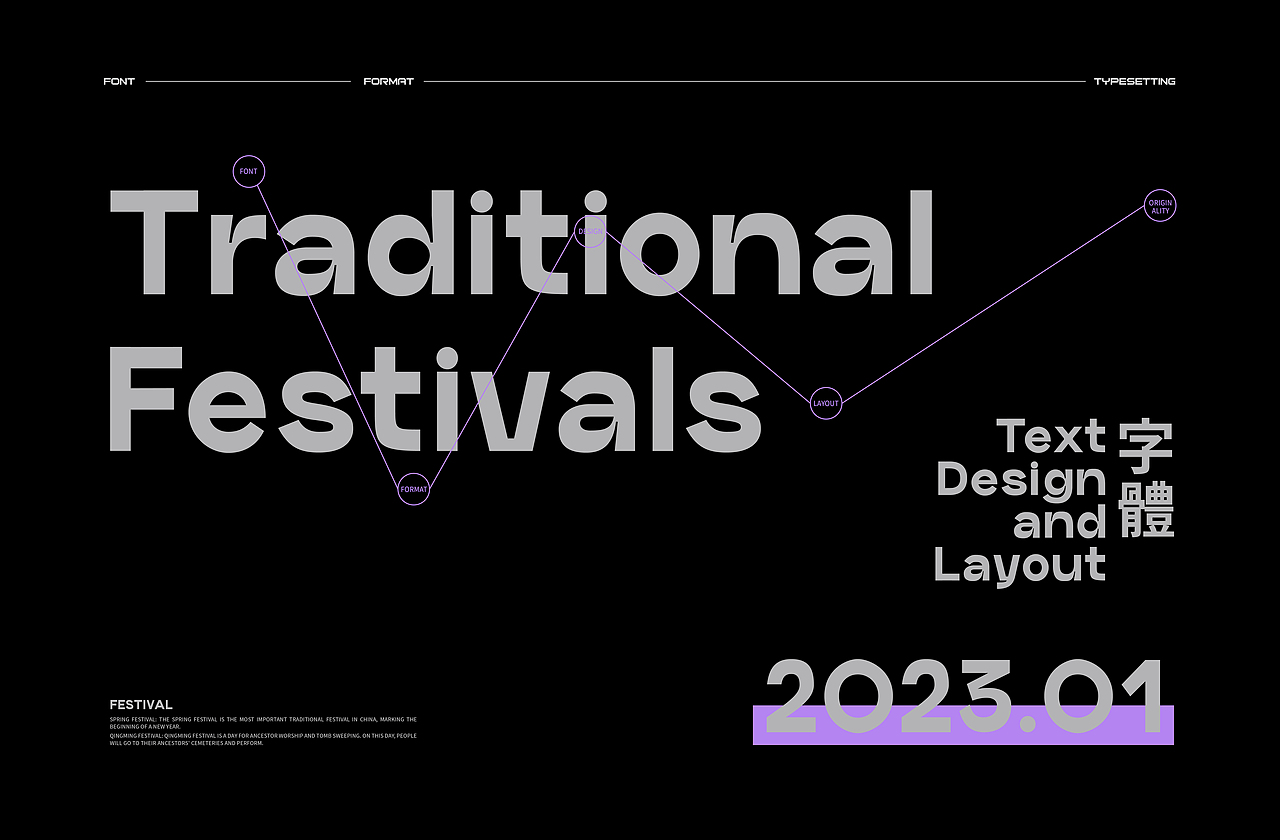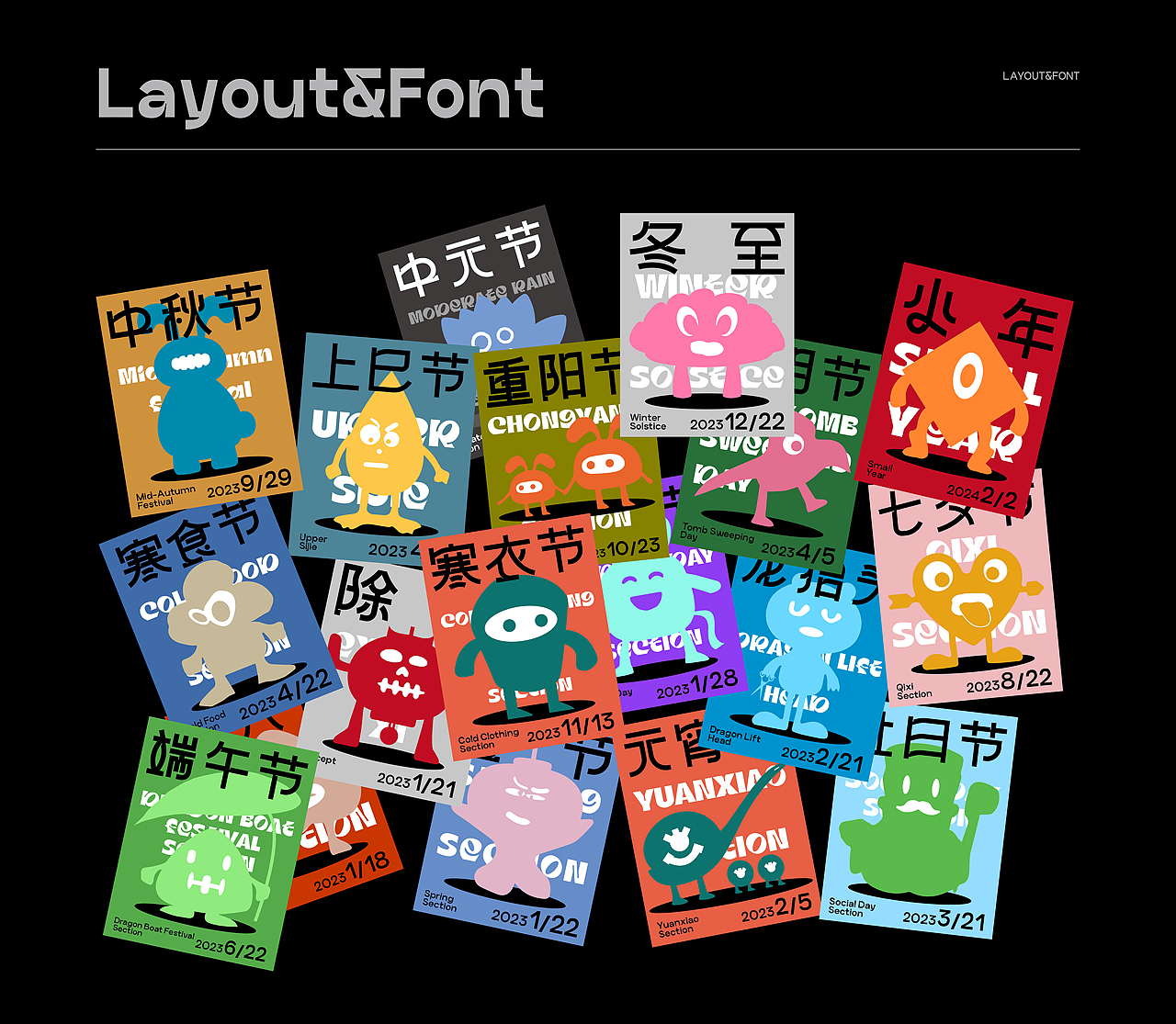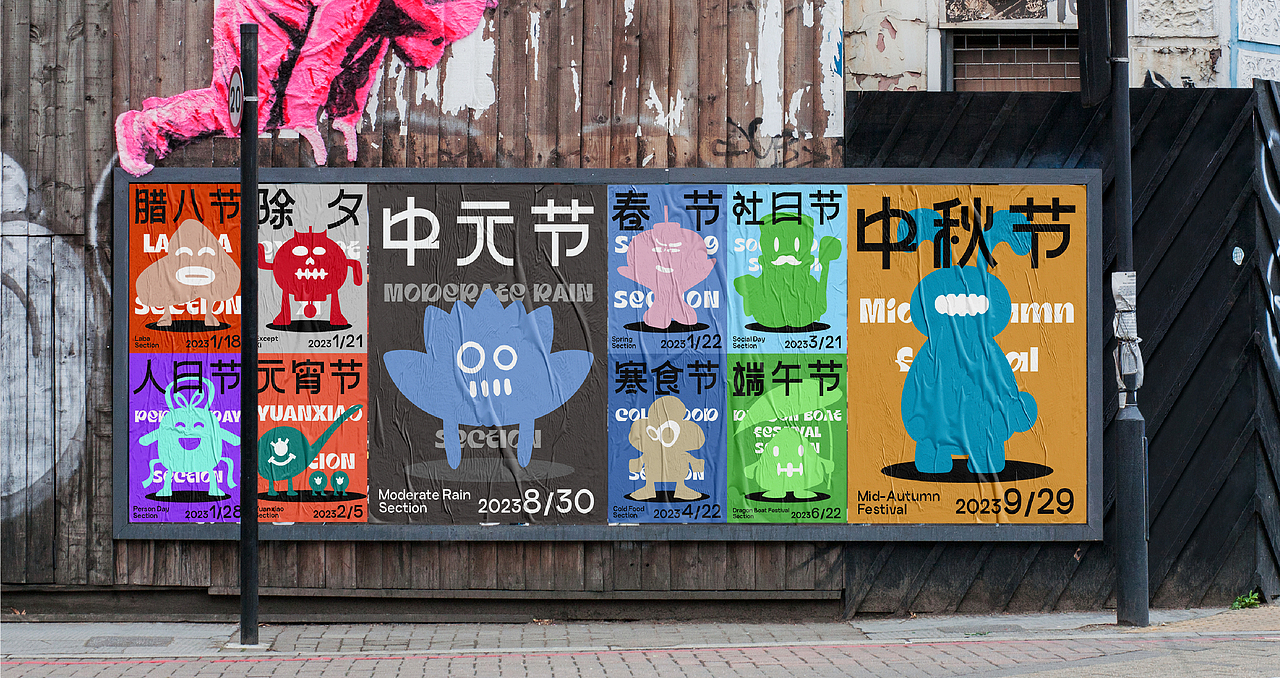
字体&版式丨中国传统节日趣味海报
中国传统节日趣味海报,通过传统节日涵义延展出趣味图形对文字设计&文字编排与构图的更多可能性。
CHINESE TRADITIONAL FESTIVAL FUN POSTERS EXPAND THE POSSIBILITIES OF FUN GRAPHICS FOR TEXT DESIGN, TEXT ARRANGEMENT, AND COMPOSITION THROUGH THE MEANING OF TRADITIONAL FESTIVALS.